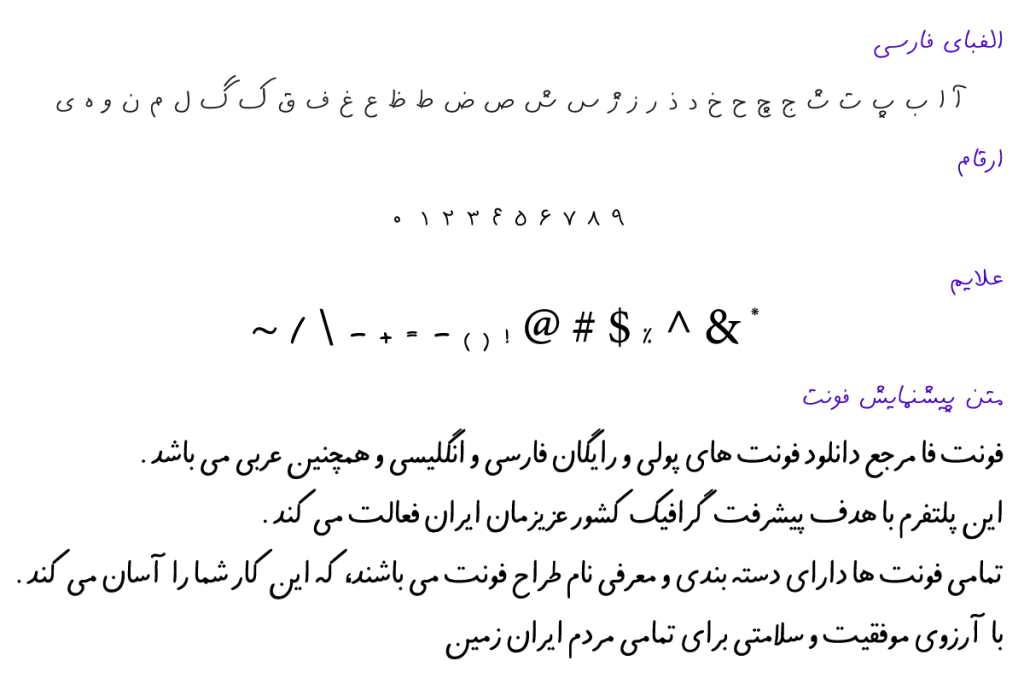
فونت فارسی بد خط – A bad khat
طراح فونت: امیر حسین صدقی نوع فونت: فونت دست نویس
توضیحات و معرفی فونت بد خط
فونت فارسی بد خط ( A bad khat ) از مجموعه فونت های سری پرشین می باشد، و نیز نوع فونت دست نویس می باشد.
فونت خوشگل مربوط توسط امیر حسین صدقی در سال 1394 طراحی و ساخته شده است که شبیه خودکار است.
و نیز فونت A bad khat در یک وزن معمولی است.
در تصویر زیر میتوانید شعر دلنشین «نام جاوید وطن» را ببینید که با این تایپ فیس فارسی طراحی شده است.